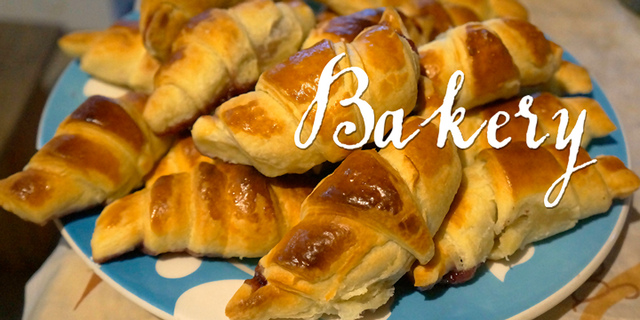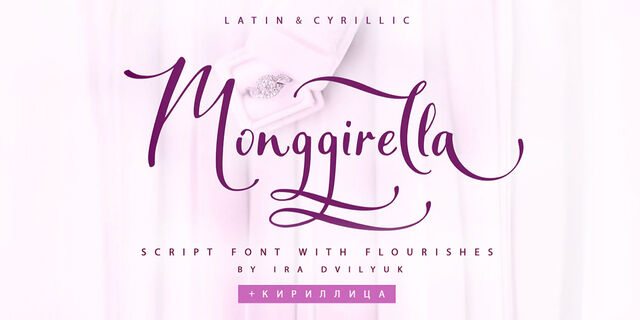
Рукописный шрифт Monggirella – это каллиграфический курсив с росчерками, который будет великолепно смотреться на всех ваших дизайнах, свадебных приглашениях, любовных письмах, материалах для брендинга, логотипах, визитных карточках, цитатах для инстаграма, фешн эскизах, каллиграфических монограммах и многом другом. Шрифт Monggirella содержит полный набор прописных и строчных букв и может использоваться для имитации каллиграфических надписей. Некоторые буквы имеют росчерки, которые вы можете получить, набрав числа после букв. Многоязычная поддержка 31 языка на основе латиницы и кириллицы.
Шрифт разработала Ирина Двилюк в 2021 году.